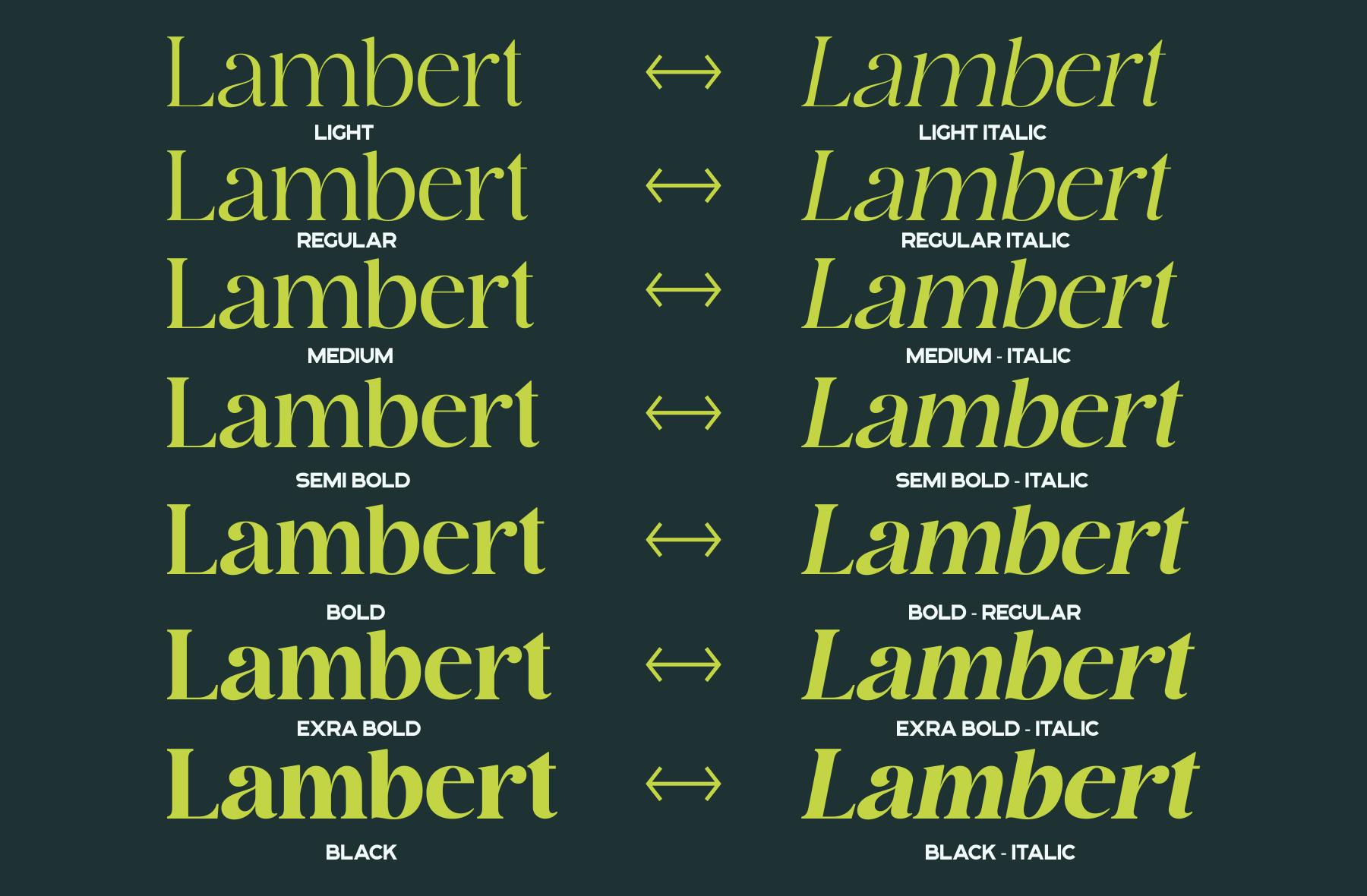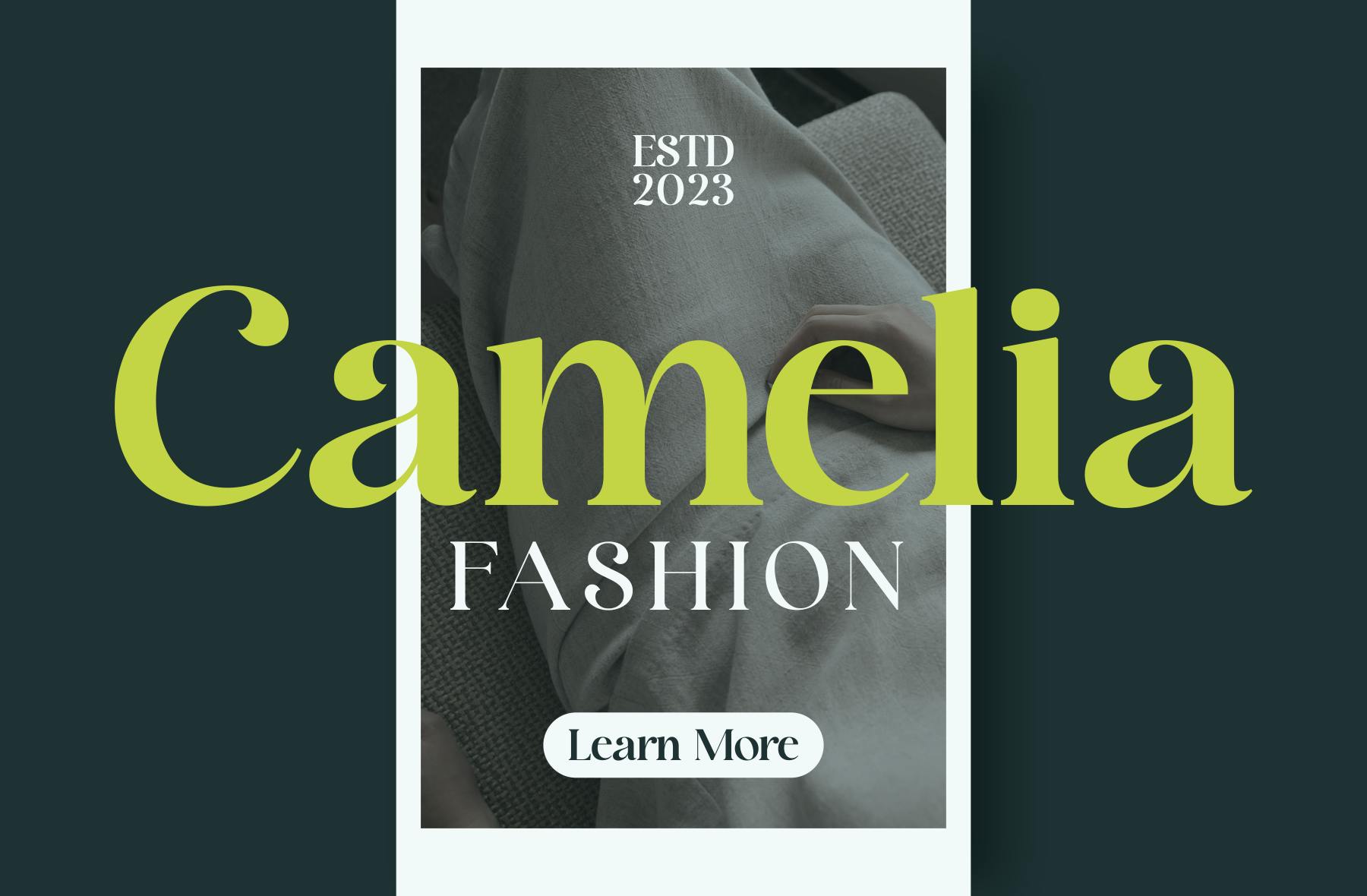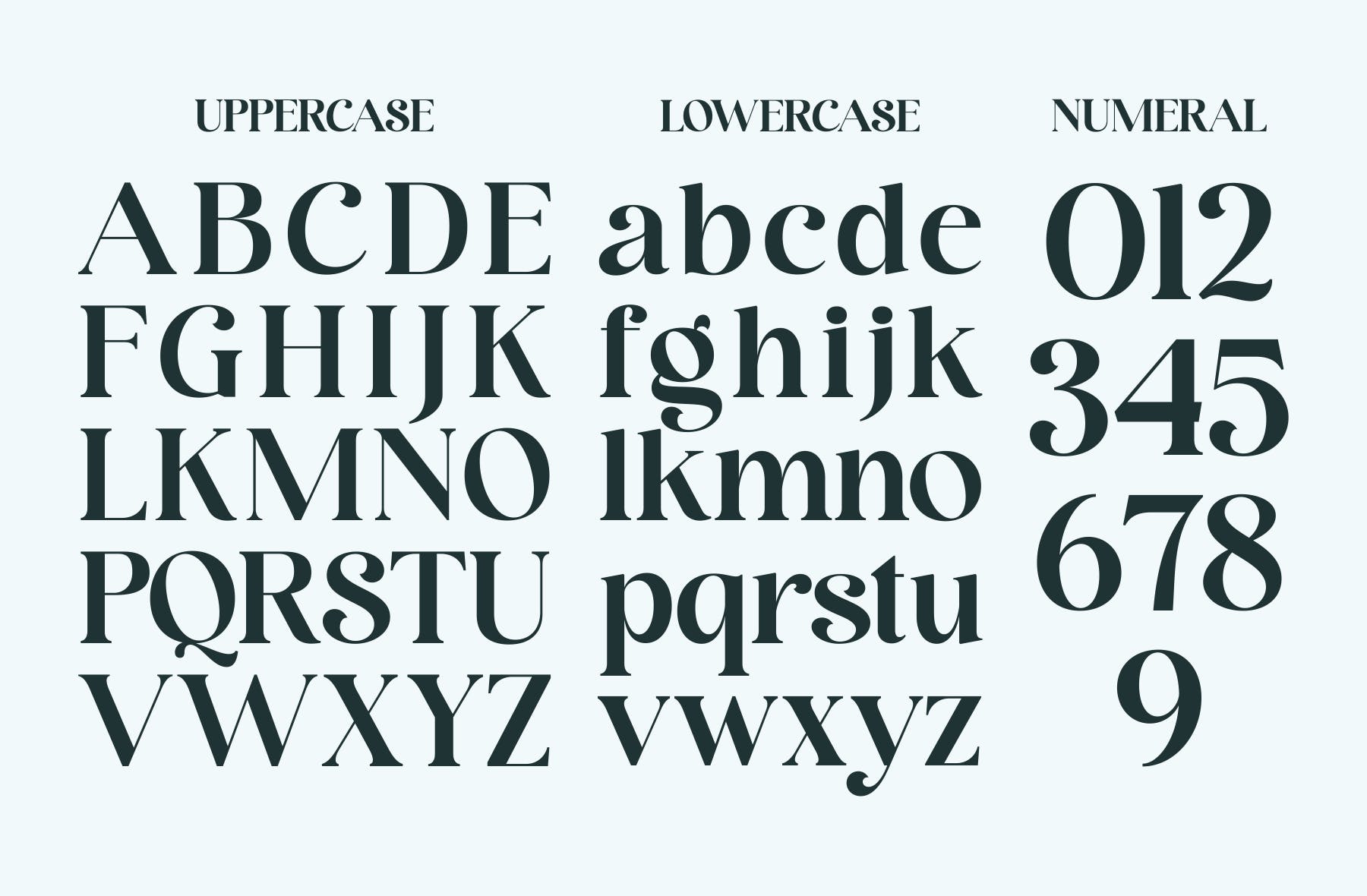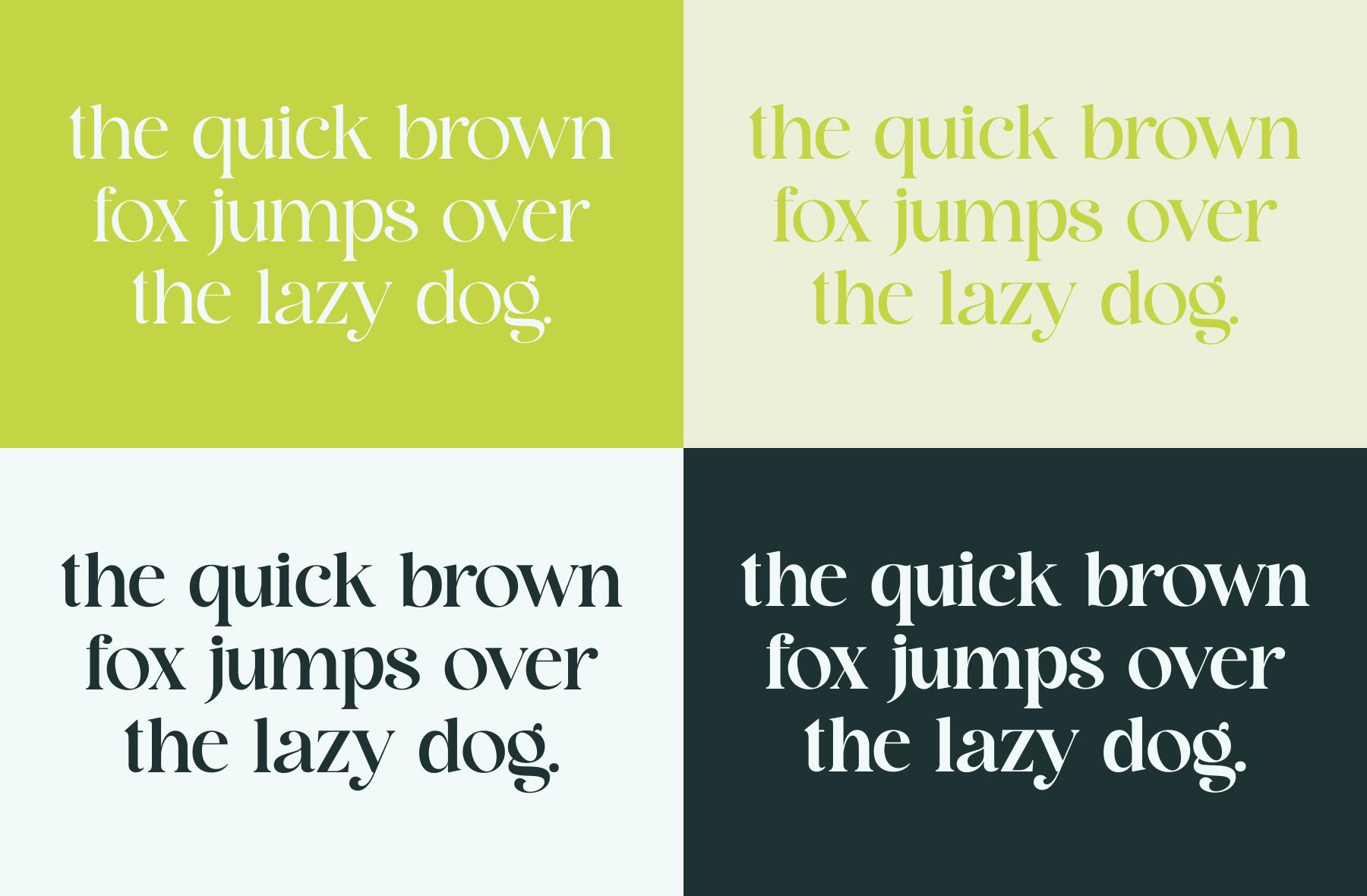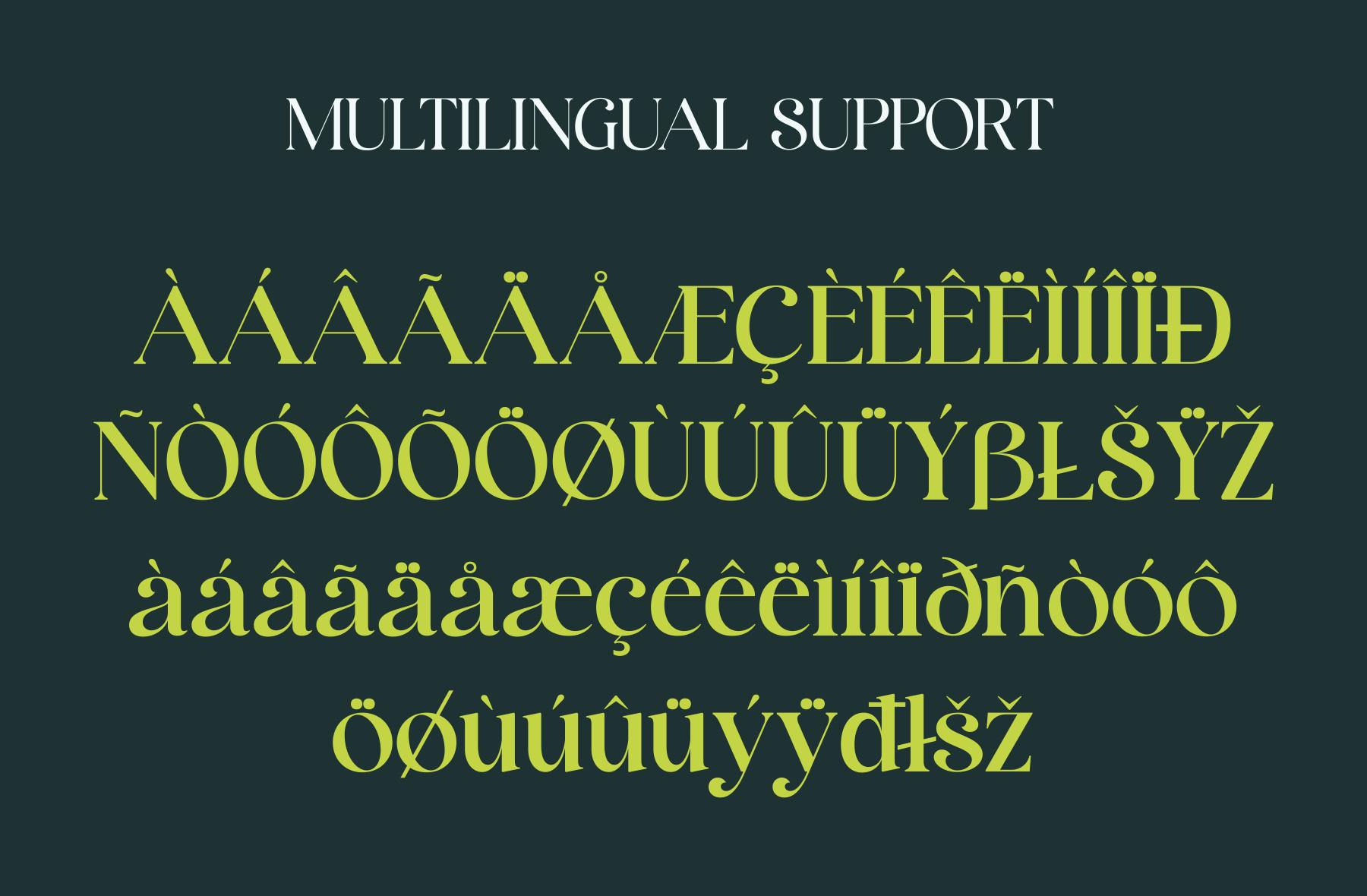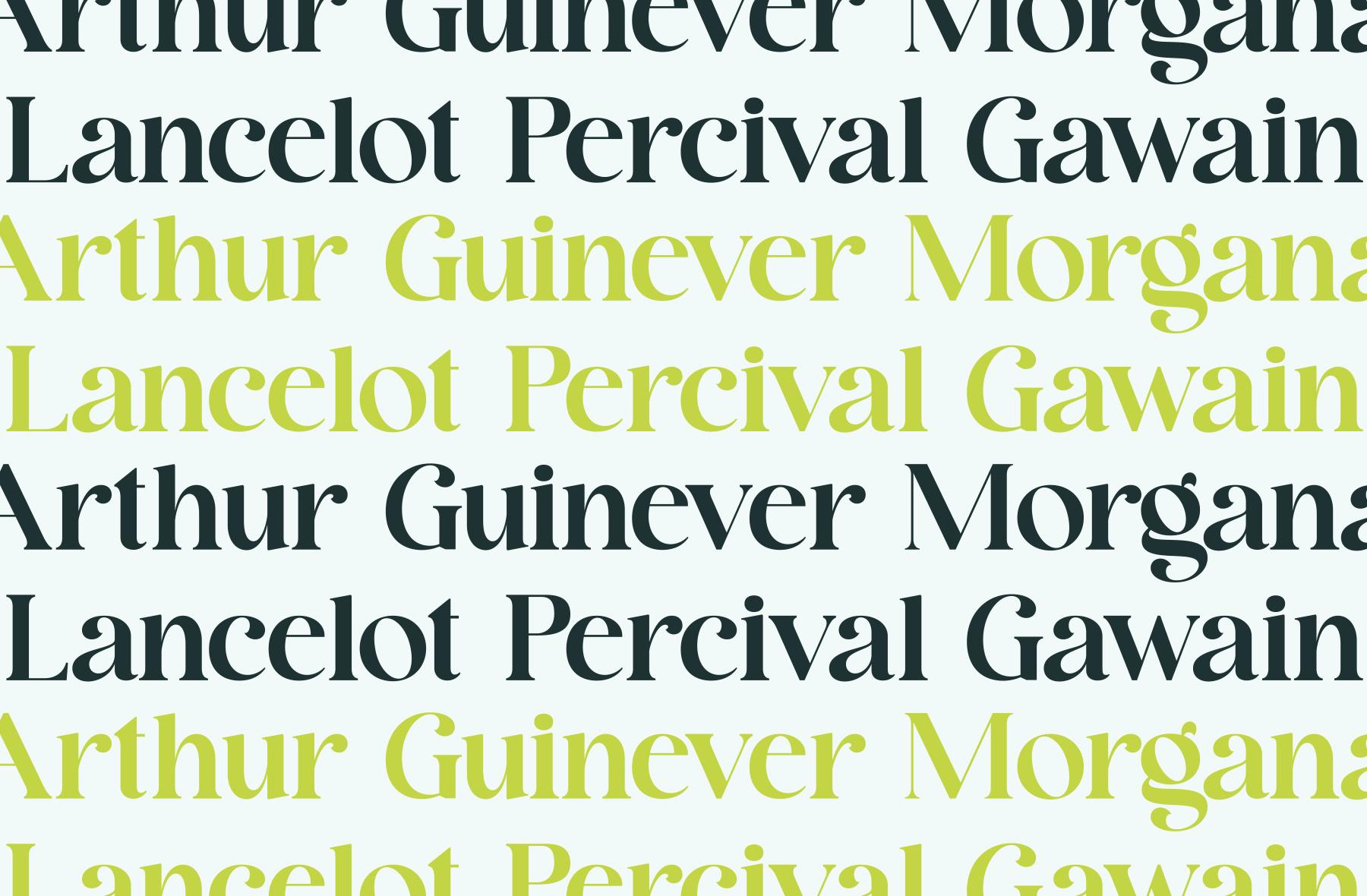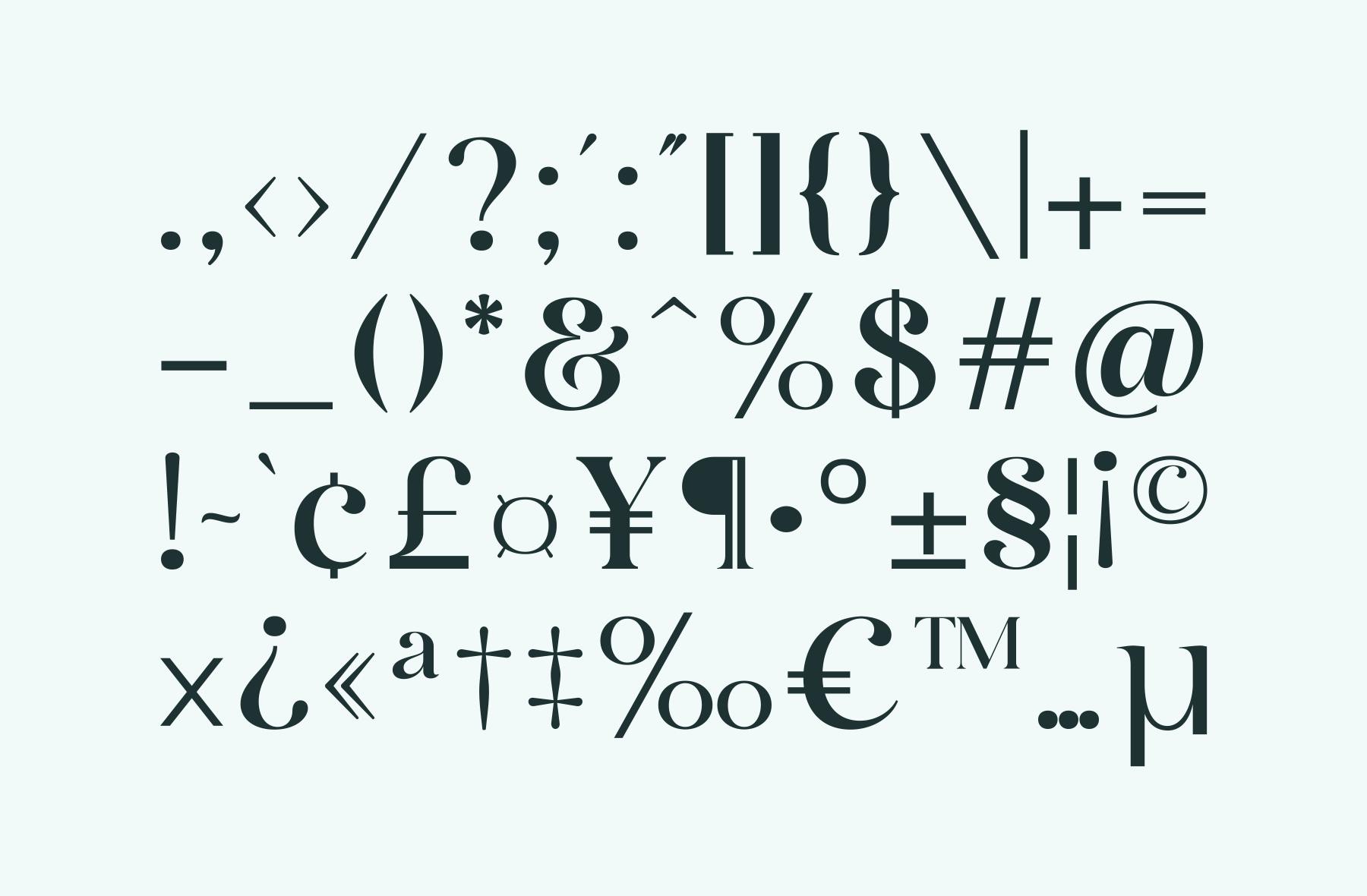
معرفی محصول جدید ما، خانواده فونت Ganos - یک فونت مدرن و جسورانه. خانواده فونت Ganos یک فونت نمایش اصیل و برجسته است که برای هر پروژه برندینگ مانند طراحی لوگو، طراحی قالب، محصولات و بسیاری دیگر مناسب میباشد. این فونت در طیف وسیعی از زمینهها برجسته و چشمنواز است.